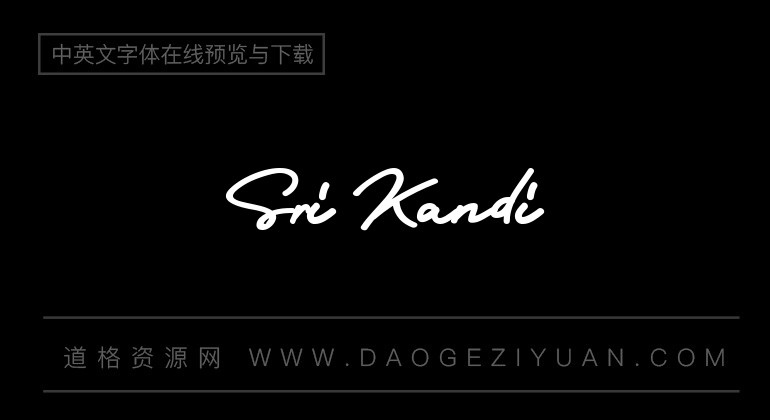
Sri Kandi
Sri Kandi是一款具有古典外观的拉丁字体,由来自印度的设计师Sri Kandi创作。这款字体具有细腻的笔画,柔和的曲线,清晰的细节和细腻的空间感,可以为你的文字提供一种精致的外观。它的特点是细腻的笔画,清晰的细节,以及极具特色的曲线,可以为你的文字提供一种优雅的外观。此外,它还具有良好的可读性,可以用于任何类型的文档和出版物。
Sri Kandi是一款非常不错的手写艺术字体,具有很好的视觉感,适合于文化类的宣传设计、商业类品牌的广告和产品包装设计以及个性化文字排版等较多场景。